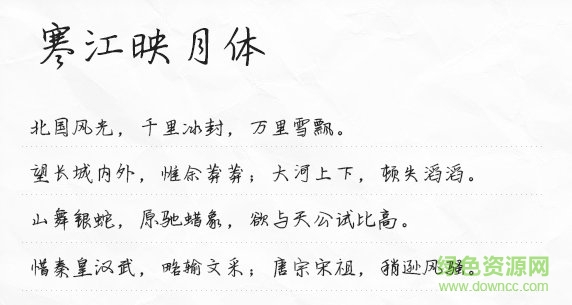
寒江映月體是一款雅致簡約的手寫字體,字庫完整,支持中文簡體輸入,能滿足大家的輸入打字需求,給你的文字增添淡泊優(yōu)雅的藝術(shù)美感,快來綠色資源網(wǎng)體驗(yàn)吧!
“湖光秋月兩相和,潭面無風(fēng)鏡未磨?!薄吃麦w。
本字庫是在國家標(biāo)準(zhǔn)簡體字庫GB2312所包含6763漢字的基礎(chǔ)上,又增加了近200常用字,已經(jīng)覆蓋了大陸99.75%的漢字使用頻率,足以滿足日常需求。
寒江映月體繼承了古風(fēng)字體的張揚(yáng)和灑脫,飛揚(yáng)而不輕浮,藝術(shù)效果十分出色,中文清秀英文清爽,無多余的點(diǎn)綴,更顯質(zhì)樸,可以運(yùn)用在藝術(shù)宣傳、文化創(chuàng)意、廣告策劃等場合。